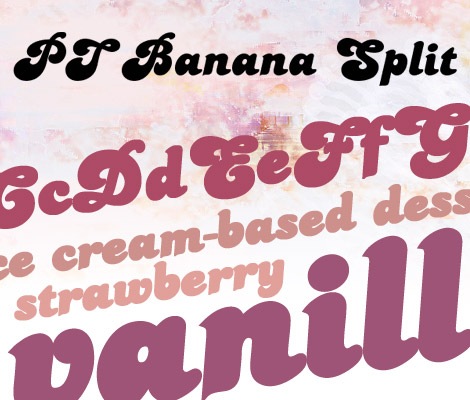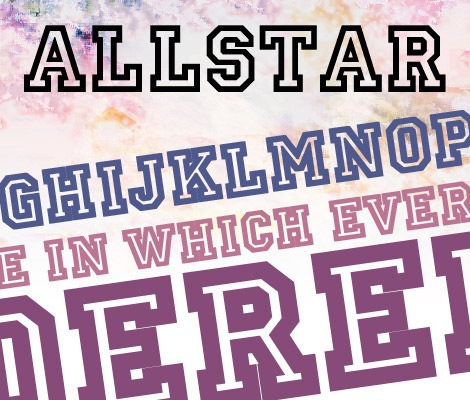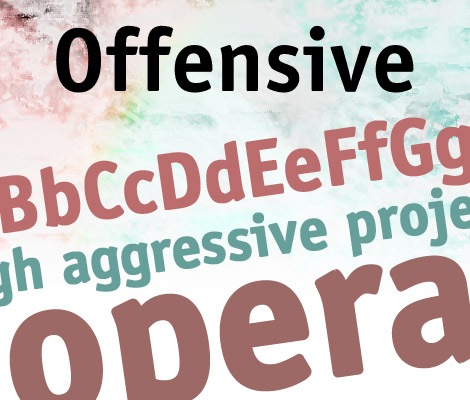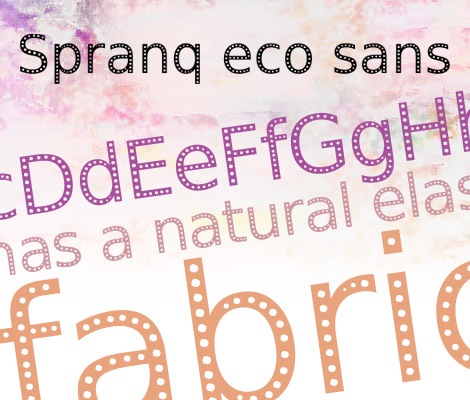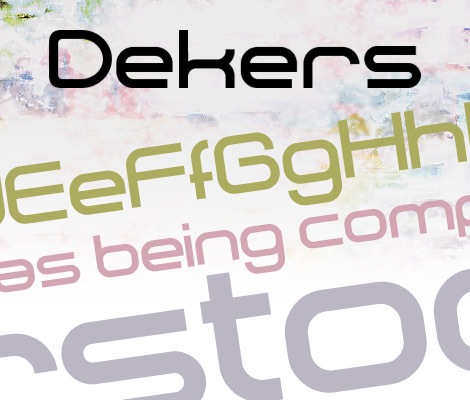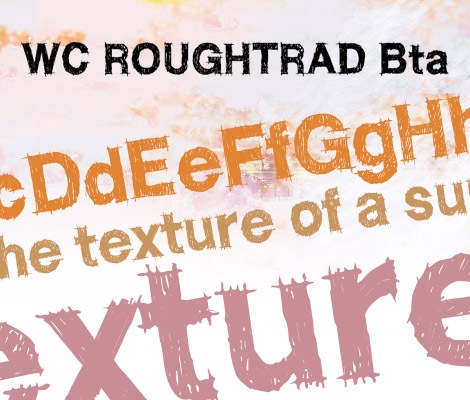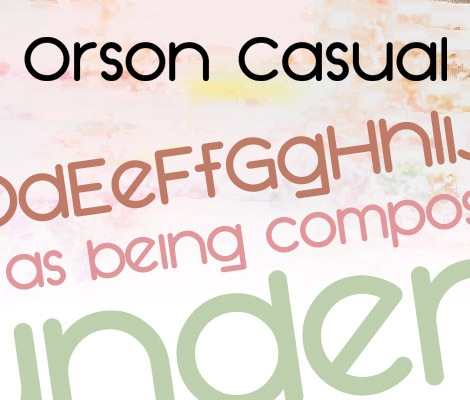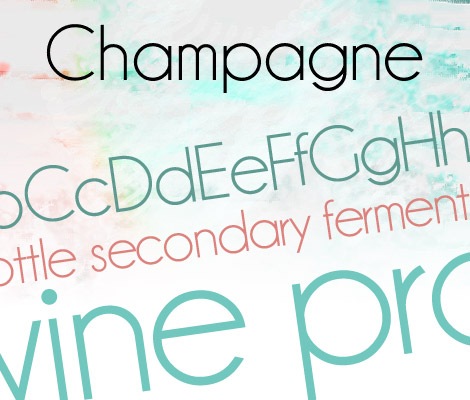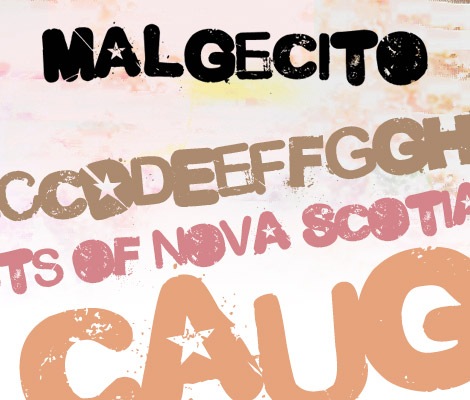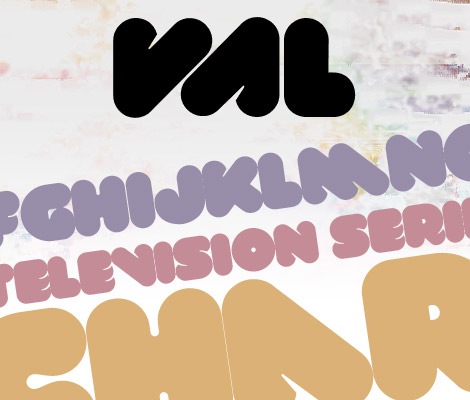
Фигурный шрифт PT Banana Split
Фигурный шрифт
Обведенный шрифт Allstar Regular
Обведенный шрифт
Шрифт Offensive Bold
Шрифт в точечку Spranq eco sans
Шрифт в точечку
Шрифт Dekers Bold
Заштрихованный шрифт WC ROUGHTRAD
Заштрихованный шрифт
Шрифт SF Orson Casual Heavy
Тонкий шрифт Champagne & Limousines
Тонкий шрифт
Стильный шрифт Malgecito
Стильный шрифт
Жирный шрифт VAL
Жирный шрифт
Шрифт Cyclo
тонкий угловатый шрифт
Угловатый шрифт Arkitech
Угловатый шрифт
Шрифт Diavlo Book
Готический шрифт Faith Collapsing
Готический шрифт
Жирный шрифт Delicious Heavy
Жирный шрифт
Шрифт с наклоном Aerovias Brasil NF
Шрифт с наклоном
Округлый шрифт Arista
Округлый шрифт
Шрифт SF Buttacup Lettering
крупный шрифт
Шрифт под названием Yanone Kaffeesatz Bold
Шрифт Saunder
узкий шрифт
Необычный шрифт Curvic
Необычный шрифт
Зарисованный шрифт karabinE
Зарисованный шрифт
Искривленный шрифт UglyQua
Искривленный шрифт
Шрифт в стиле гранж Requiem
Шрифт в стиле гранж
Прописной шрифт CurlyJoe
Прописной шрифт
Шрифт “от руки” Yelly
Шрифт “от руки”
Шрифт NK122
печатный шрифт
Шрифт под названием Decker
полный шрифт
Шрифт Sansumi Bold
обычный шрифт
Шрифт Santana Bold
шрифт с необычными буквами